Das 11. Seminar »Typografie intensiv«
Wie war’s, Die Frage an jedem Seminarabend, am Ende des ersten Moduls; besonders spannend für uns. Notiert hatte ich unter anderem: Freude über das neue Lernen; spannend sind die verschiedenen Ansichten der Teilnehmerinnen; spannende Gruppe; anstrengende Theorie, so viele Bilder, wieso so viel Theorie, kann man doch selbst nachlesen; macht Spaß endlich wieder schneiden und kleben; wo sind die Regeln (Rezepte); abwechslungsreich – Theorie und Praxis ausgeglichen; echte Chance, voneinander lernen …
Einführung, Grundlagen, Gestaltungsbasis
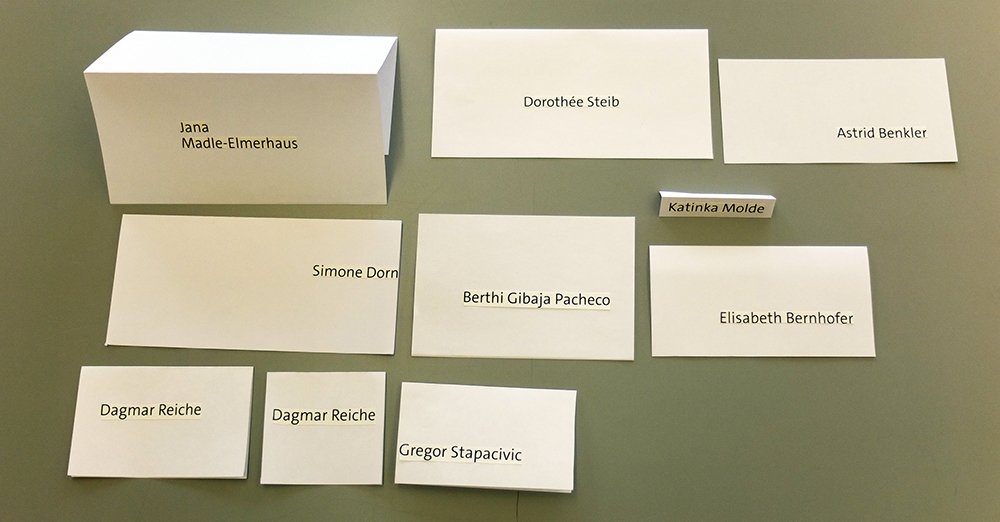
In der Einführung geht es um die Struktur des Seminars, was Typografie überhaupt alles kann, wie wichtig die manuelle Technik des Gestaltens sein kann, was konzeptionelles Denken vermag. Eine Einführung in das Scribblen bei Entwürfen folgt vor der Diskussion der Basis von Raum und Gestaltung und der Mikrotypografie. Ein Vortrag über Typografie im 20. Jahrhundert, hier das bauhaus, schließt das 1. Modul ab. Es traf sich, dass an diesem Tag die tgm 125 Jahre alt wurde und alle Seminarteilnehmerinnen zum Fest eingeladen waren .
Mikrotypografie Basis
Mikrotypografie ist die Basis für eine funktionierende, gut lesbare und auch attraktive Typografie. Auch wer schon glaubt, alles zu wissen, ist oft erstaunt wie viel es da noch gibt. Und dann wird das Gelernte auch gleich noch probiert.
Mikrotypografie hängt natürlich mit dem Makrobereich zusammen, also dem Seitenaufbau und der Komposition von Seiten. Wichtige Theorieteile in diesem Modul sind »Lesbarkeit von Schrift und Typografie« (ein Thema, mit dessen Forschungsaspekten ich mich intensiv auseinandersetze). Und ein Exkurs gilt der Geschichte der Schrift ab Gutenberg. Die ersten Hausarbeiten werden besprochen.
Makrotypografie, Seitenaufbau
Makrotypografie bedeutet, daß man sich mit der Logik der Seitengestaltung und der typografischen Visualisierung befasst. Das ist umfassend und gut einsichtig anhand der Buchgestaltung. Es geht um die Frage, was wir aus der Geschichte der Buchgestaltung heute lernen und sogar übernehmen können. In einer Hausarbeit geht es um die Rekonstruktion einer klassischen Textbuchgestaltung. Nur eine Rekonstruktion, aber für viele beinhaltet das wieder sehr viel Neues. Dagmar Nathalie Gorbach bespricht die Aufgaben und diskutiert sie vor allem in allen Phasen intensiv mit den Teilnehmerinnen. Die Sehnsucht nach dem selber machen ist groß, manchmal ist die Ungeduld im Weg.
Dass Makrotypografie bisweilen weit in Komposition, Funktion und Attraktivität reichen kann, erläuterten wir anhand der von uns gestalteten Hitler, Mein Kampf-Edition.
Schrift: Basis, Schriftwahl, Schriftarten
Die Druckschriften als zentrales Thema am ersten Tag mit Oliver Linke, der einen weiten Bogen spannt: Schrift und der Zusammenhang zum Schreiben, aus der Geschichte der lateinischen Buchstaben, die Formmerkmale der Schriften und ein Überblick über die heutigen digitalen Schrifttechniken. Es folgt eine Übersicht über die Klassifikation der Druckschriften, Zusammenhänge von Schriftfamilien, Schriftsippen und eventuellen Schriftmischungen. Besonders wichtig: Aspekte der Schriftwahl. Neben den Schriftskizzen als Hausarbeit gibt es noch eine besondere Aufgabe: Ein Geschenkpapier nur aus typografischen Elementen entwickeln.
In den Diskussionen zeigte sich, dass die Mikrotypografie enormen Einfluss auf die Wirkung der Schrift hat.
Mikro- und Makrotypografie und strategisches Arbeiten mit InDesign
Mit diesem Modul sind wir ganz dicht an der Praxis und damit auch am Alltag: Mikro- und Makrotypografie mit InDesign, geleitet von Catherine Avak. Jetzt geht es darum, die gelernte Basis auch richtig anzuwenden. Das beginnt mit strategischen Vorüberlegungen und behandelt alle Aspekte detailierter Typografie-Anwendung unter InDesign. Natürlich ist das kein Basiskurs InDesign. Auf die Basis wird aufgesetzt. Und das Ganze hat mitunter ein rasantes Tempo.
Komposition und Gestaltung
Die Basis des Gestaltens: Was bedeutet Komposition auf der Fläche. Was kann mit oder durch die Theorien der Flächengestaltung erreicht werden? Analytisches Sehen und Wahrnehmen im Hinblick auf die gestaltete Welt. Und alles beginnt mit einfacher Gestaltung, die für Typografie fast immer dominant ist. Exkurse gehen zu Kandinskys Theorie »Punkt, Linie und Fläche« und zahlreiche praktische Basisübungen unterbrechen den Theoriestrom. Diese Übungen verlassen bisweilen die zweidimensionale Dimension und haben recht viel mit Wahrnehmung zu tun. Einblicke in die Typografie des 20. Jahrhunderts ergänzen gezielt den Stoff des Moduls. So ist die Arbeit von Emil Ruder in Basel für uns grundlegend und auch aus der Schweiz kommend der begriff der »Integralen Gestaltung«.
Am Abend ging es noch weiter: Sabine Noak von Römerturm Feinstpapier hilt ein mehrstündiges Seminar über Papiersorten und Veredelungstechniken.
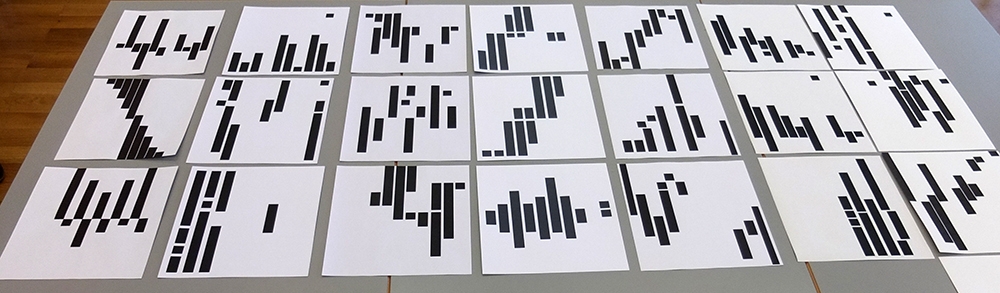
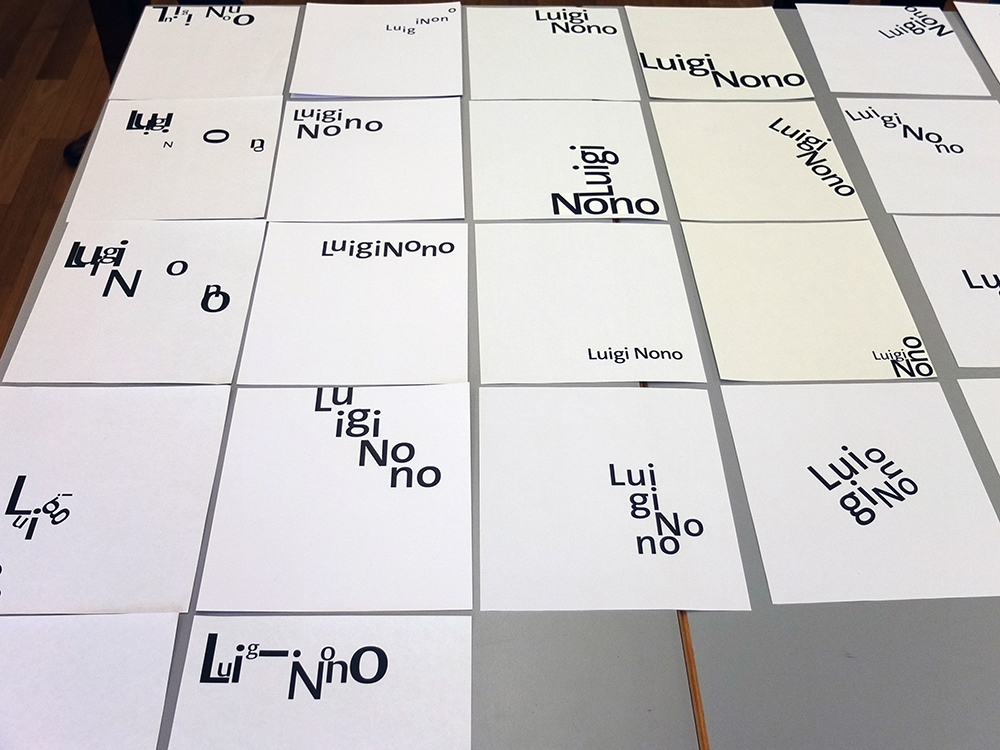
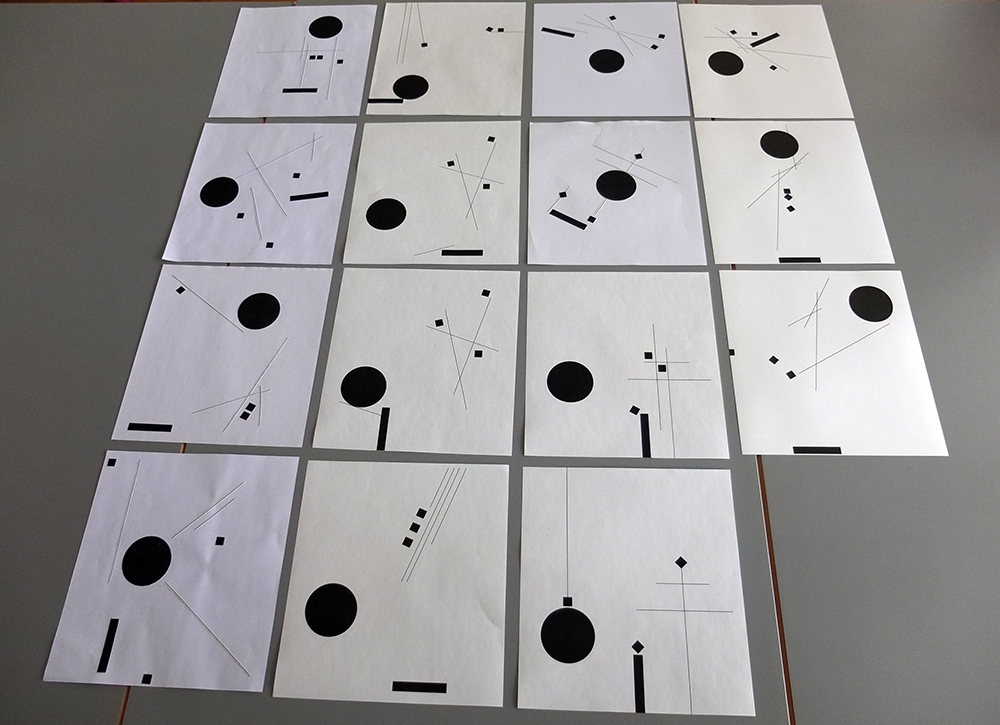
Farbe, Gestaltung und Wahrnehmung
Ein ganzes Modul geht nur um Farbe. Das bedeutet zunächst einiges an Basistheorie. Der Aufbau und die Bedeutung der Grundfarben, Kontrastmöglichkeiten, das Sehen von Farben. Vor allem visuelle Farbprogramme und die Bedeutung der Farbe für die Schrift werden erläutert. Der zweite Tag ist dagegen sehr praktisch angelegt. Ilona Amann geht nach einer knappen, aber gezielten Einführung ans Werk. Jetzt heißt es Farben aussuchen, vergleichen, selber Farben mischen und eine Übung folgt der anderen, ein intensiver Farb-Workshop.
Das tägliche Blitzlicht zum Abend finden wir eine wichtige Ergänzung der Kommunikation untereinander. Manchmal ist Erleichterung, oder Freude dabei, bisweilen wird auch »Dampf abgelassen«. Anhand der Aufzeichnungen daraus steht unsere Arbeit immer auf dem Prüfstand. Schließlich hat sich unser Seminar seit der Gründung 1990 kontinuierlich weiter entwickelt. Der Anspruch ist auf allen Seiten gestiegen und trotz Jahrhunderte langer Gestaltungsgeschichte bewegen wir uns in der heutigen Zeit.